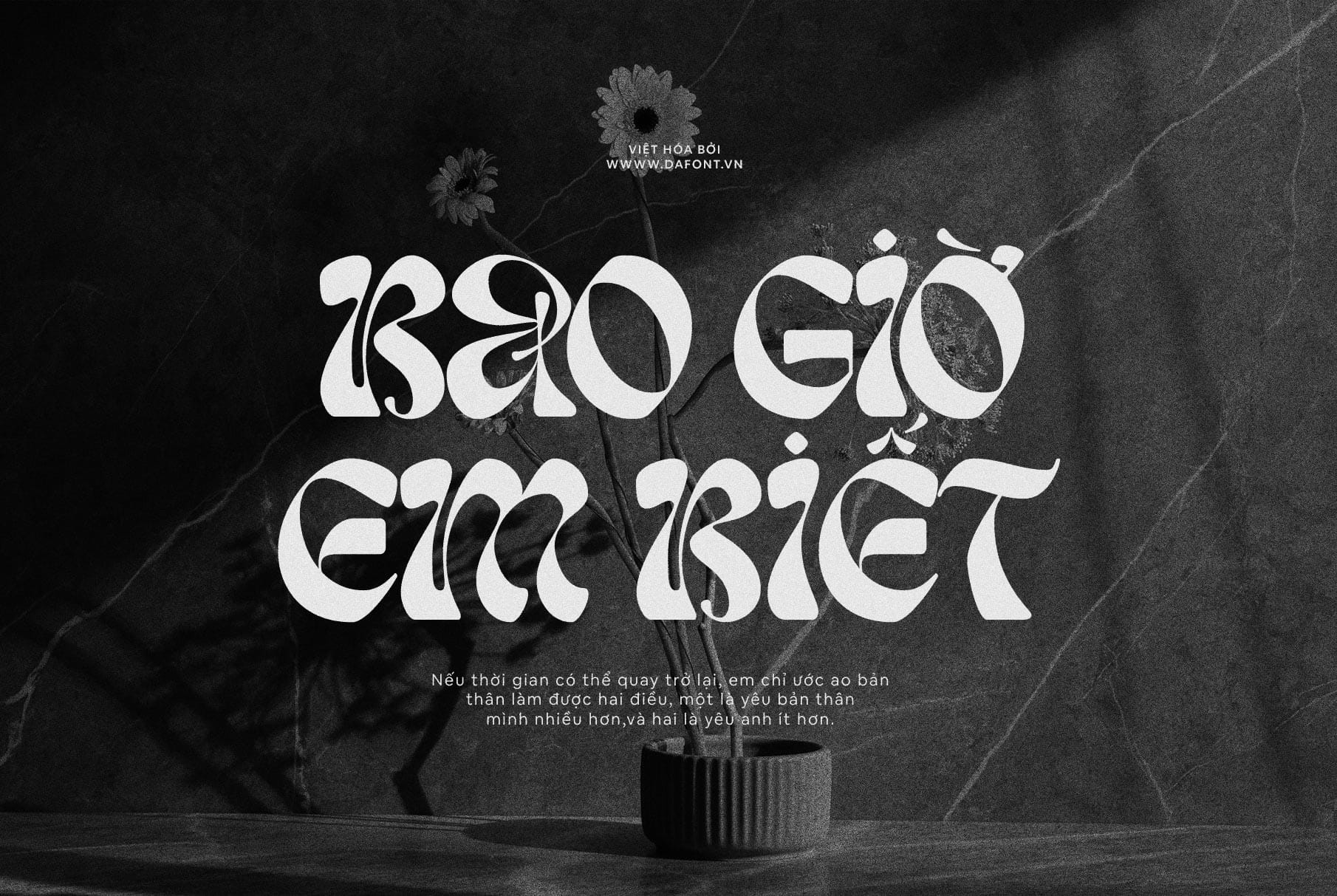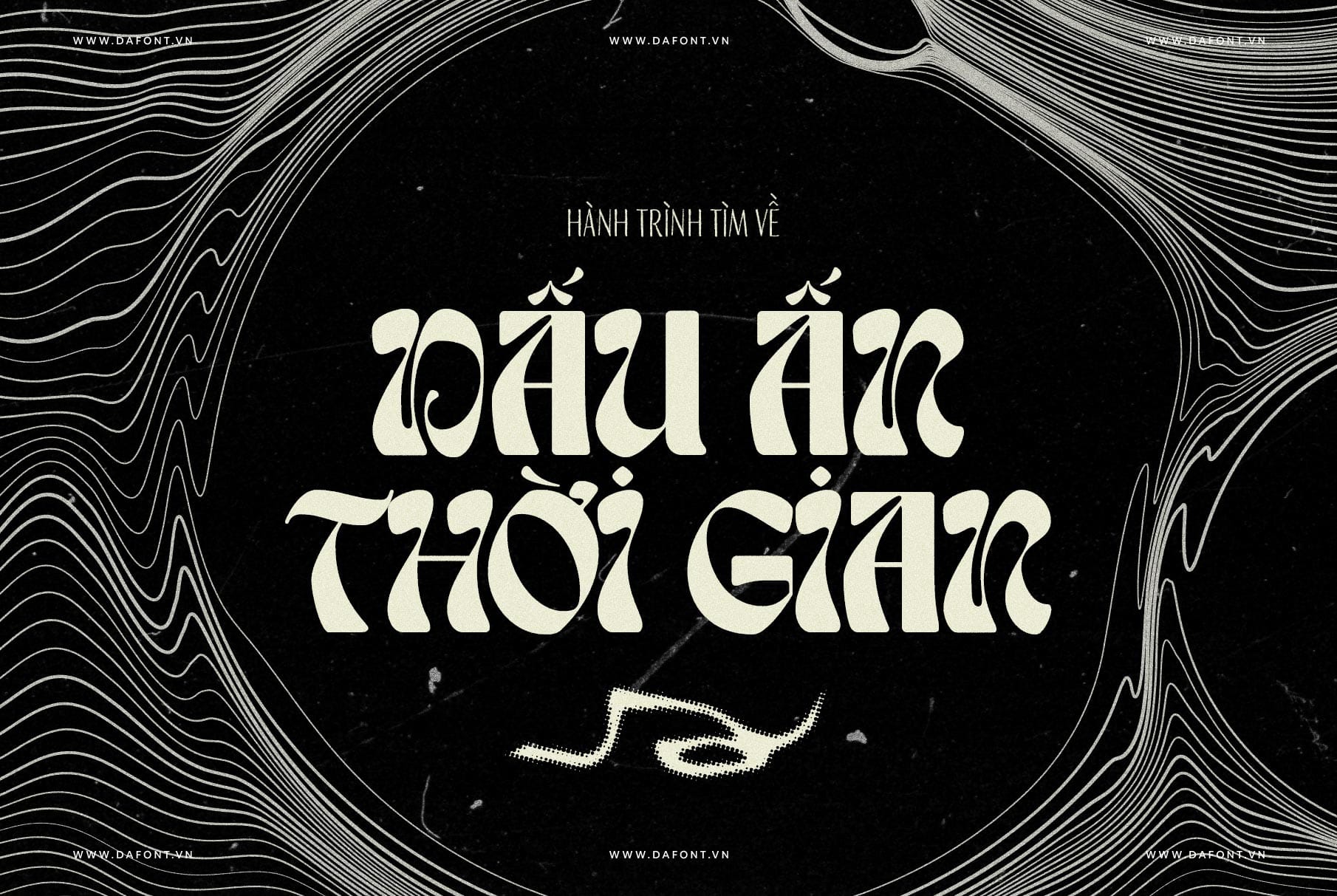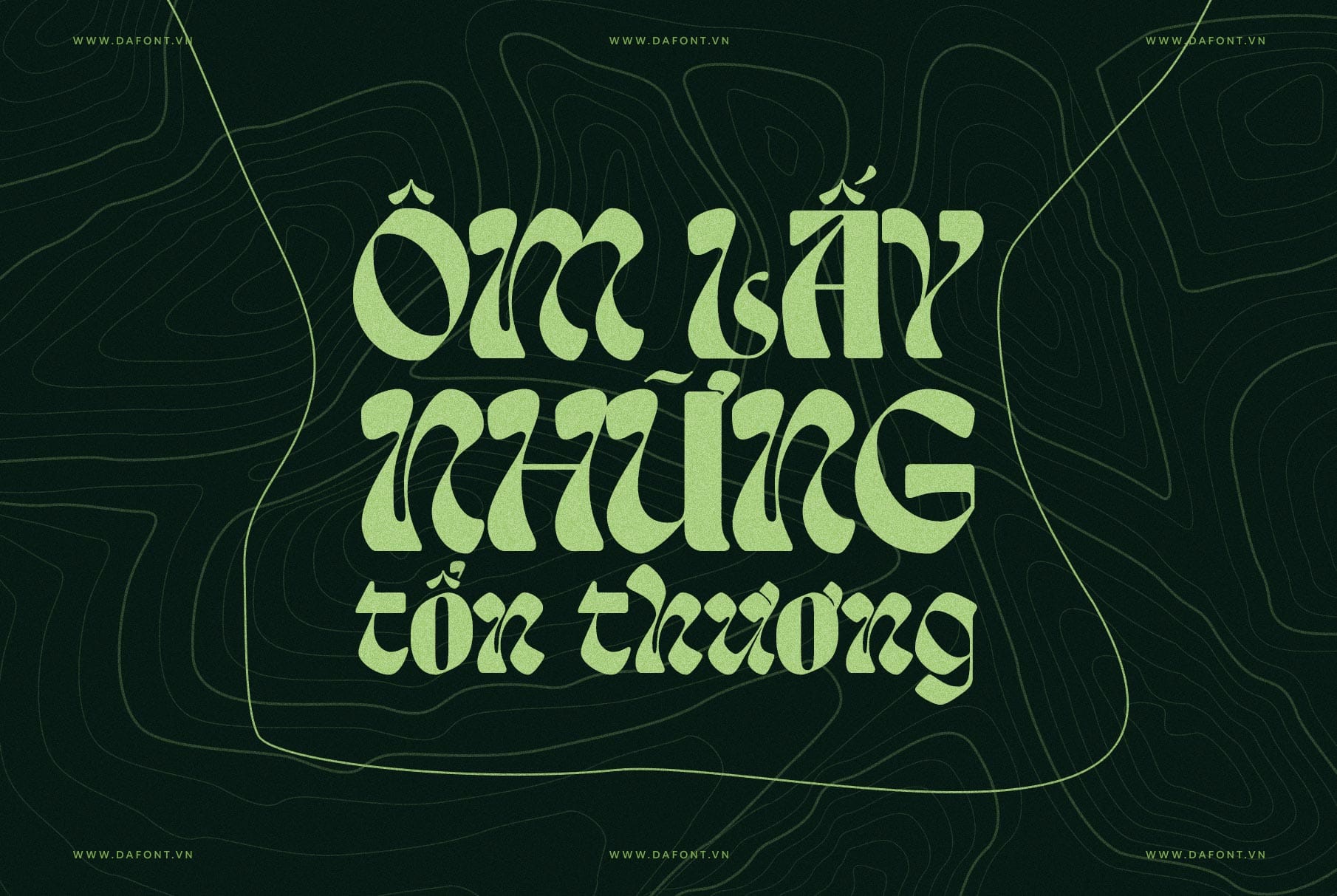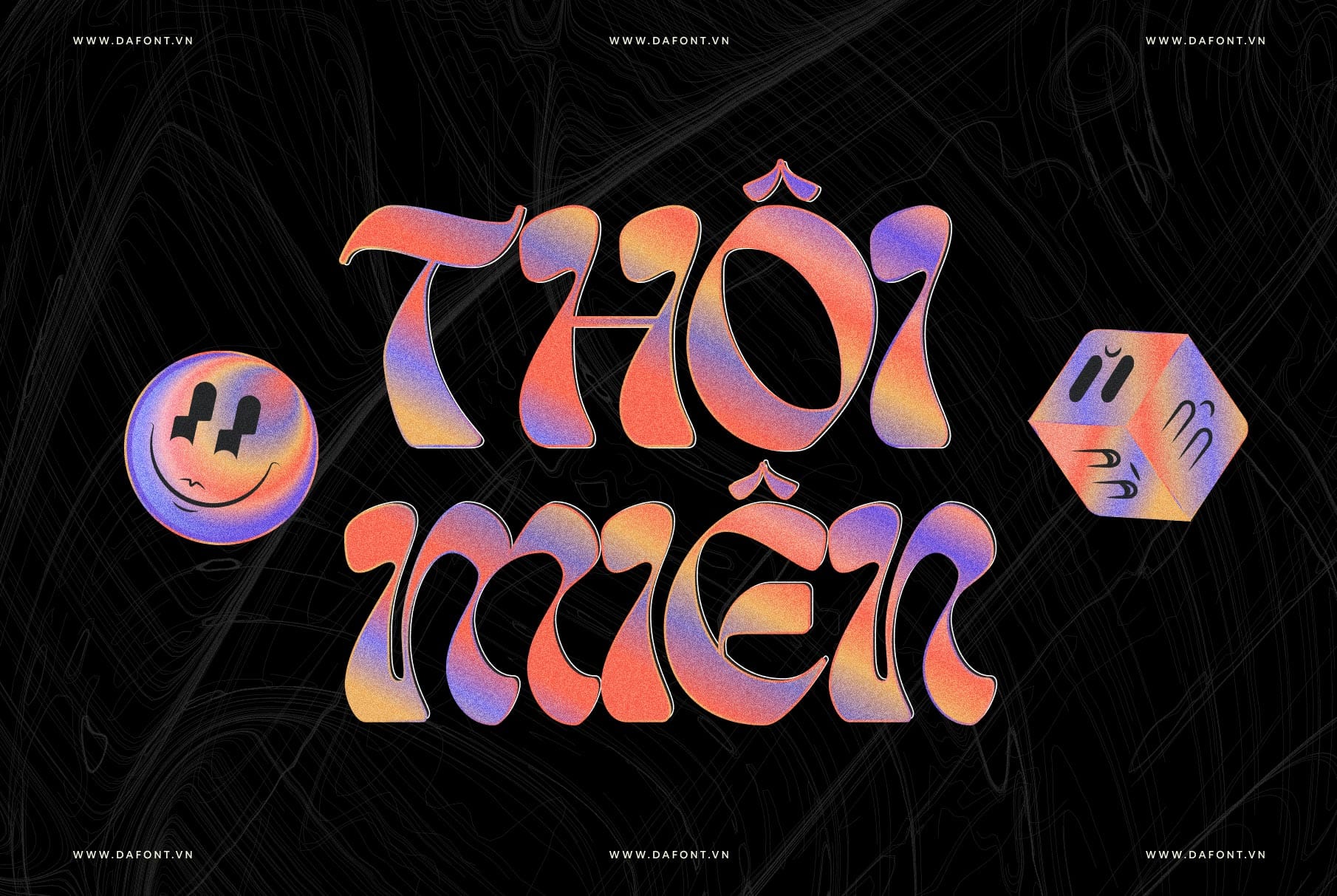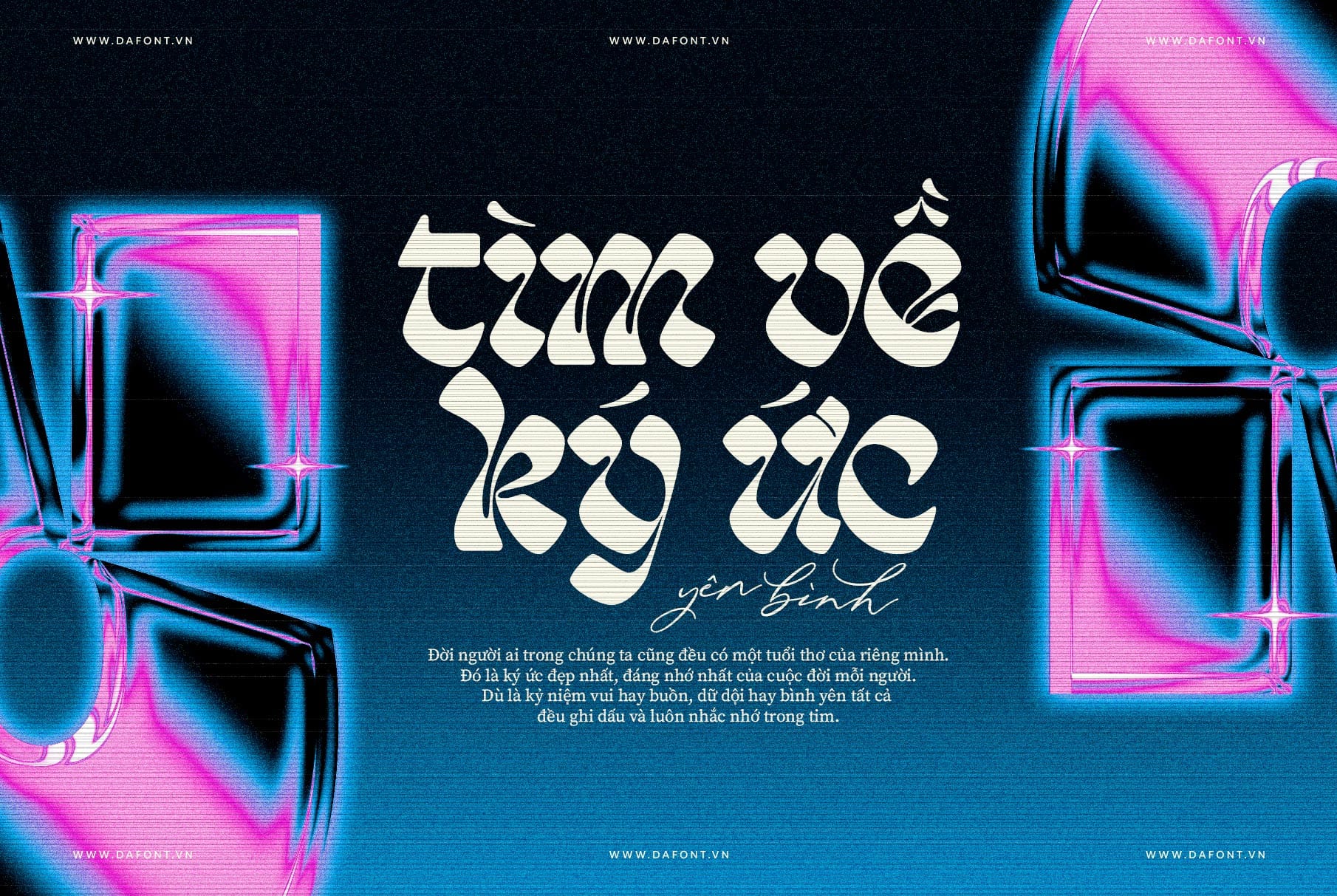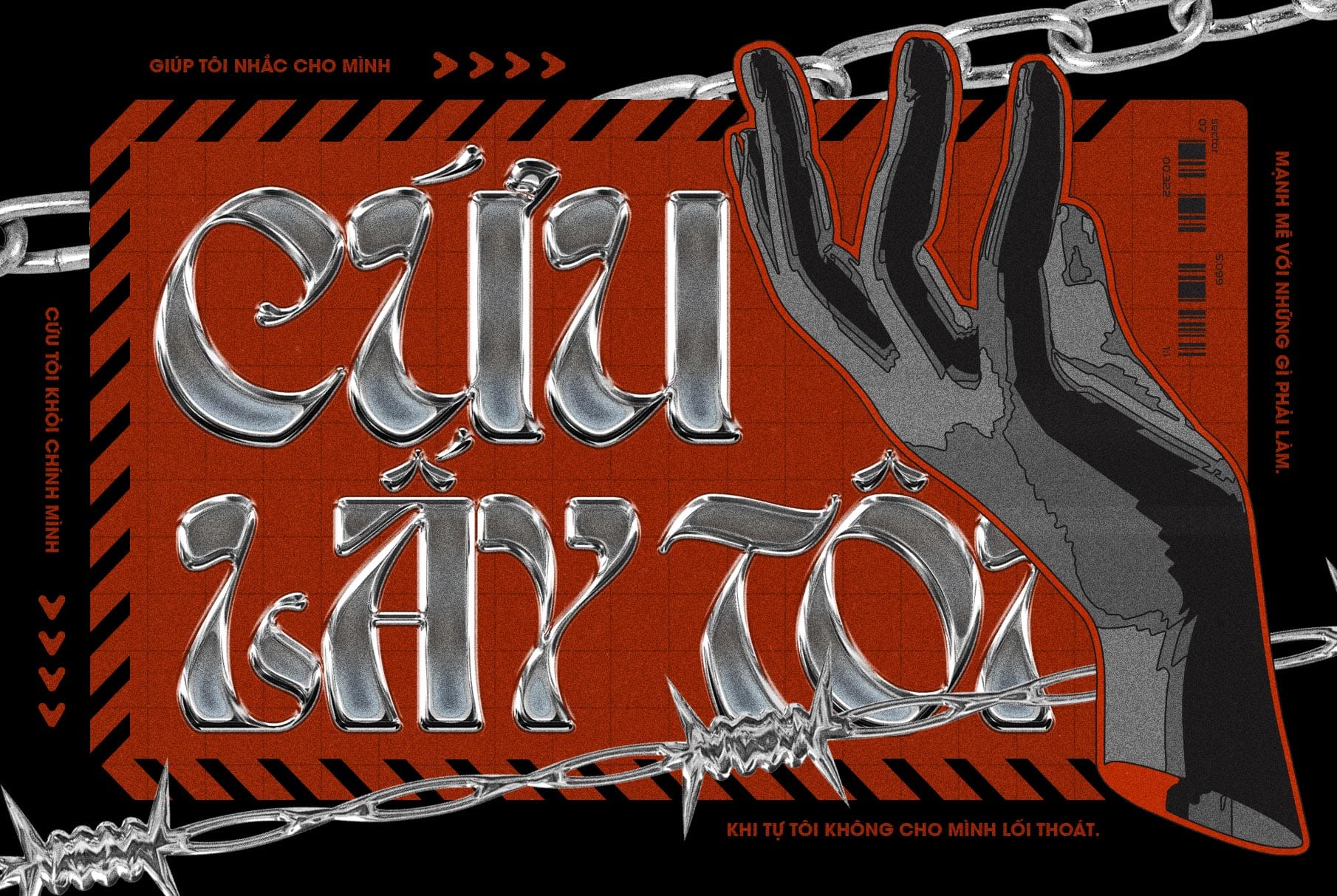
DFVN TAN – TUESDAY là một kiểu chữ độc đáo, lấy cảm hứng từ phong cách blackletter cổ điển, kết hợp với tính cách sôi động và phong cách retro đầy cuốn hút. Loại font này đặc biệt thích hợp cho những dự án thiết kế có tính chất sáng tạo cao, muốn truyền cảm hứng retro đặc trưng.
Điểm nổi bật DFVN TAN – TUESDAY
TAN – TUESDAY không chỉ đơn thuần là một kiểu chữ, mà còn là một công cụ sáng tạo mạnh mẽ dành cho các nhà thiết kế. Với sự kết hợp giữa phong cách truyền thống và hiện đại, loại font này mang đến nhiều tính năng nổi bật, giúp bạn dễ dàng tạo ra những sản phẩm thiết kế cuốn hút, độc đáo và khác biệt.
1. Phong cách Blackletter hiện đại
TAN – TUESDAY mang đặc trưng của phong cách blackletter truyền thống, nhưng được biến tấu để trở nên gần gũi và phù hợp hơn với xu hướng hiện đại.
2. Phong cách retro sôi động
Font chữ này kết hợp hoàn hảo phong cách retro và đương đại, mang lại sự pha trộn độc đáo cho các dự án thiết kế để bạn có thể nổi bật giữa đám đông.
3. Dễ dàng tích hợp
TAN – TUESDAY thích hợp với nhiều ngữ cảnh thiết kế: từ poster, bao bì sản phẩm, logo cho đến các giao diện kỹ thuật số.
Phong cách độc đáo và nổi bật
Nếu bạn đang tìm kiếm một font chữ mạnh mẽ để nâng cao chất lượng thiết kế, DFVN TAN – TUESDAY chính là sự lựa chọn lý tưởng. Với phong cách độc đáo và khả năng tích hợp linh hoạt, font chữ này không chỉ giúp tạo ra các sản phẩm thiết kế đột phá mà còn nâng tầm giá trị thẩm mỹ cho dự án của bạn.
- Táo bạo và sáng tạo: TAN – TUESDAY phù hợp cho những nhà thiết kế muốn đạt đến cái nhìn táo bạo và khác biệt.
- Tạo ấn tượng mạnh mẽ: Phong cách độc đáo của font chữ này mang lại ấn tượng khó phai, giúp thương hiệu hoặc sản phẩm trở nên khác biệt.
- Tính linh hoạt cao: DFVN TAN – TUESDAY dễ dàng tích hợp với nhiều phong cách thiết kế, giúp bạn tạo ra những tác phẩm đắc sắc nhất.
DFVN TAN – TUESDAY – Đậm chất retro
DFVN TAN – TUESDAY không chỉ là một font chữ, mà còn là nguồn cảm hứng cho những ai muốn khám phá phong cách thiết kế độc đáo. Nếu bạn đang tìm kiếm một giải pháp thiết kế mới mẻ, đậm chất retro, DFVN TAN – TUESDAY chính là sự lựa chọn hoàn hảo.